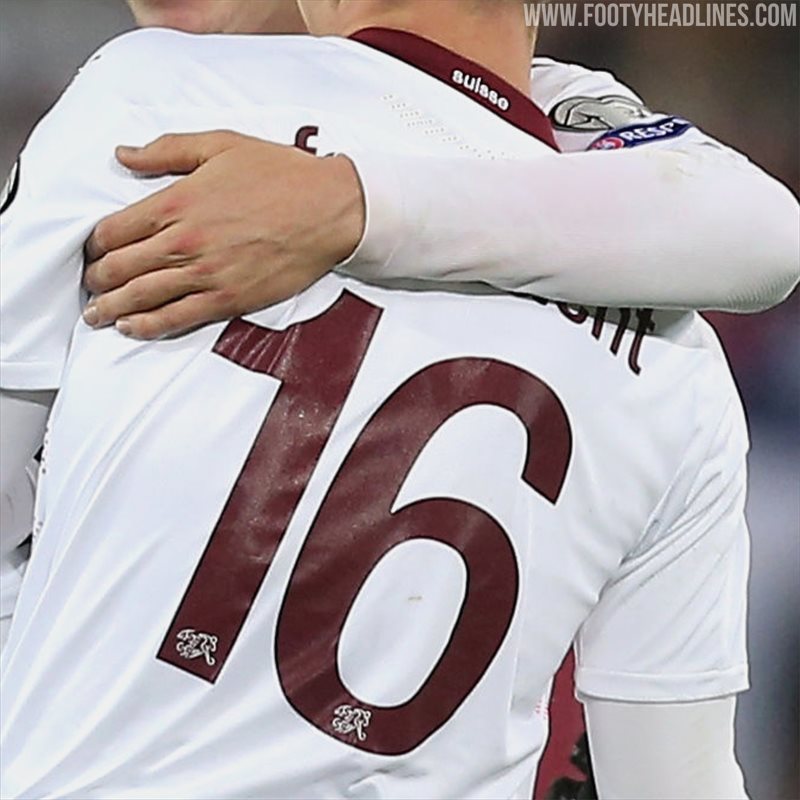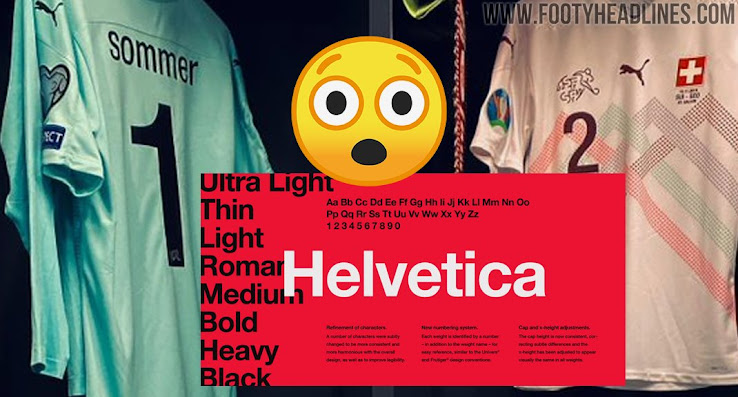
Unglaublich?! Schweiz EM 2020 Trikot-Schriftart ist nur "Windows" Helvetica Schriftart
Die Schweiz debütierte ihr brandneues Auswärtstrikot für die EURO 2020 im Qualifikationsspiel zu Hause! gegen Georgien. Damit bekamen wir einen ersten Blick auf die neue Schriftart, die Puma für die EM 2020 Trikots der Schweiz entworfen hat.
Schweiz EM 2020 Trikot-Schriftart
Die neue Schweiz EM 2020 Trikot-Schriftart von Puma hat keinen individuellen Look. Es ist einfach die berühmte Helvetica-Schriftart - das einzige maßgeschneiderte Element der Schweiz EM 2020 Trikot-Schriftart ist das Logo des Schweizerischen Fussballverbandes am unteren Ende der Zahlen.
Obwohl es auf den ersten Blick sehr langweilig von Puma zu sein scheint, gibt es einen kniffligen Grund, warum Puma sich für diese Schrift entschieden hat.
Die Helvetica oder "Neue Haas Grotesk" ist eine weit verbreitete serifenlose Schrift, die 1957 vom Schweizer Schriftgestalter Max Miedinger mit Unterstützung von Eduard Hoffmann entwickelt wurde.
Warum hat sich Puma dann für die Schrift entschieden? Helvetica ist Lateinisch und heißt auf Deutsch "Schweiz" und sie wurde auch von einem Schweizer Schriftdesigner entworfen. Ziemlich clever.
Die neue Schweiz EM 2020 Trikot-Schriftart soll auch für das Heimtrikot verwendet werden.